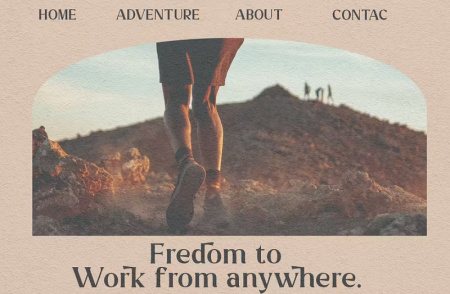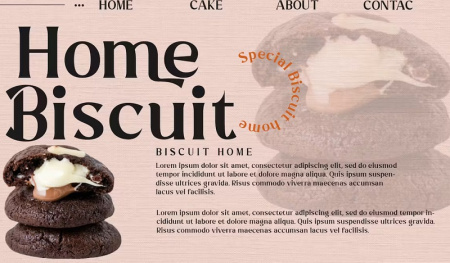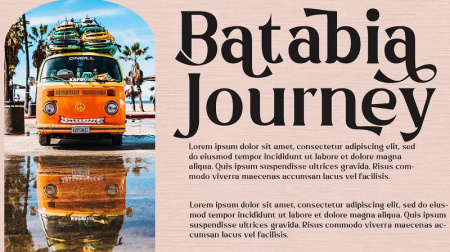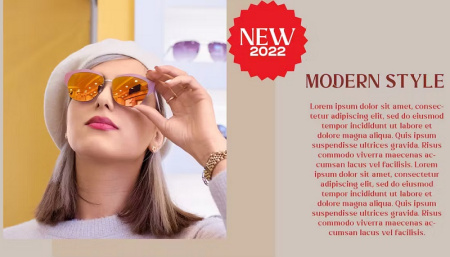
فونت انگلیسی Blankcho
فونت انگلیسی Blankcho یک فونت انگلیسی زیبا در نسخه ساده است. این فونت انگلیسی مناسب برای تایپوگرافی های لوکس، طراحی لوگوهای مدرن، وب سایت ها، نقل قول های رسانه های اجتماعی، نام تجاری عروسی و موارد مناسب است. برای مشاهده تصاویر این مجموعه و دانلود فونت انگلیسی از جی اف ایکس دانلود به ادامه مطلب مراجعه کنید.
✅ همه حروف بزرگ
✅ علائم نگارشی و شماره،
✅ لیگاتورها و جایگزین ها
✅ پشتیبانی چند زبانه ÀÁÂÃÄÅÆÇÈÉÊËÌÍÎÏÐÑÒÓÔÕÖØÙÚÛÜÝ